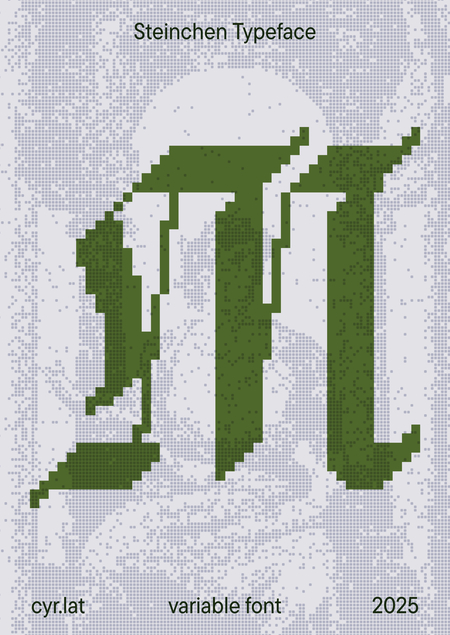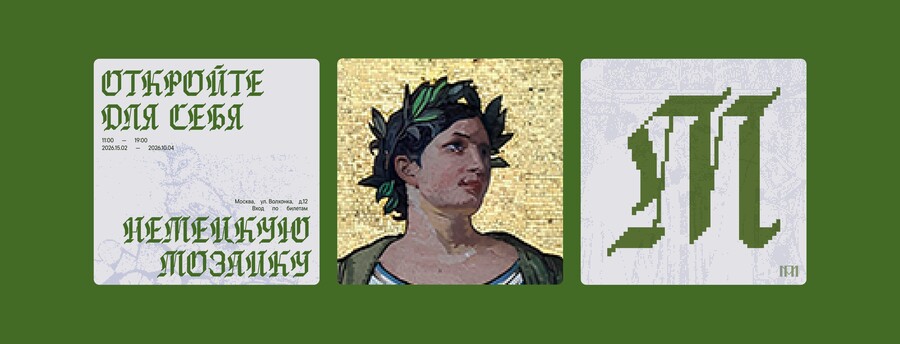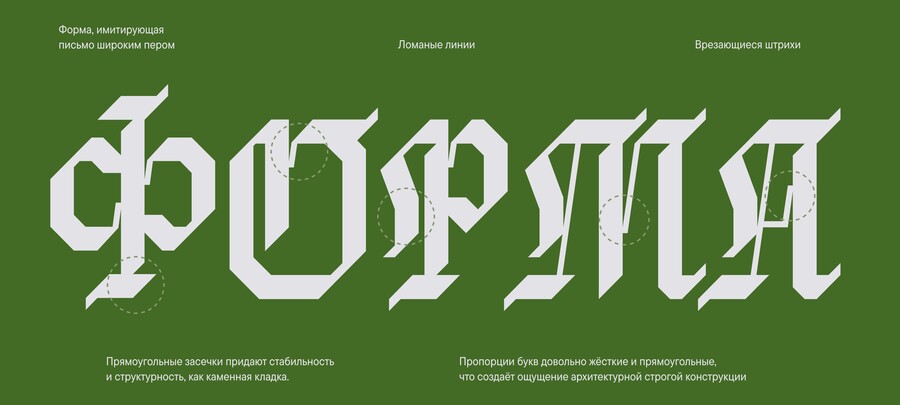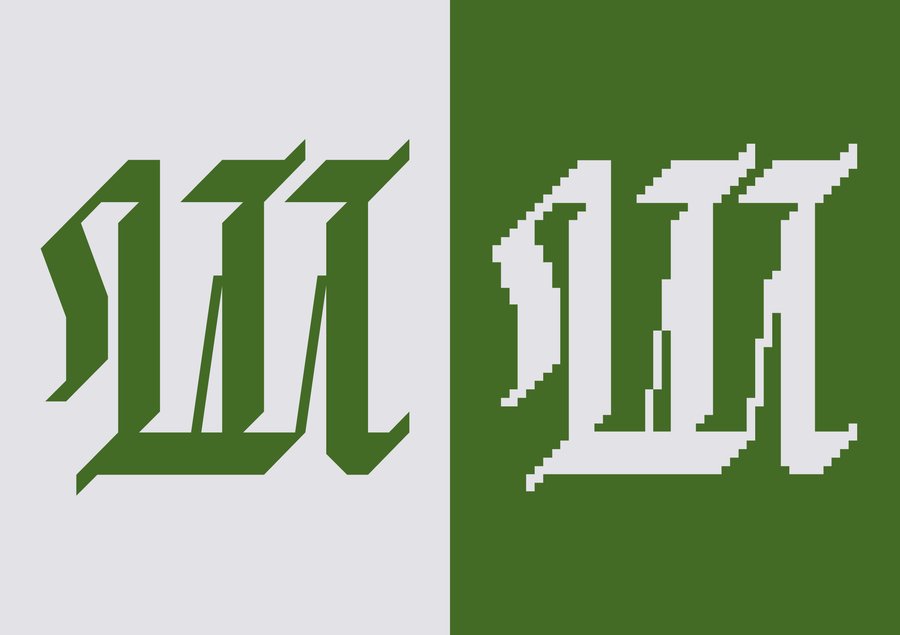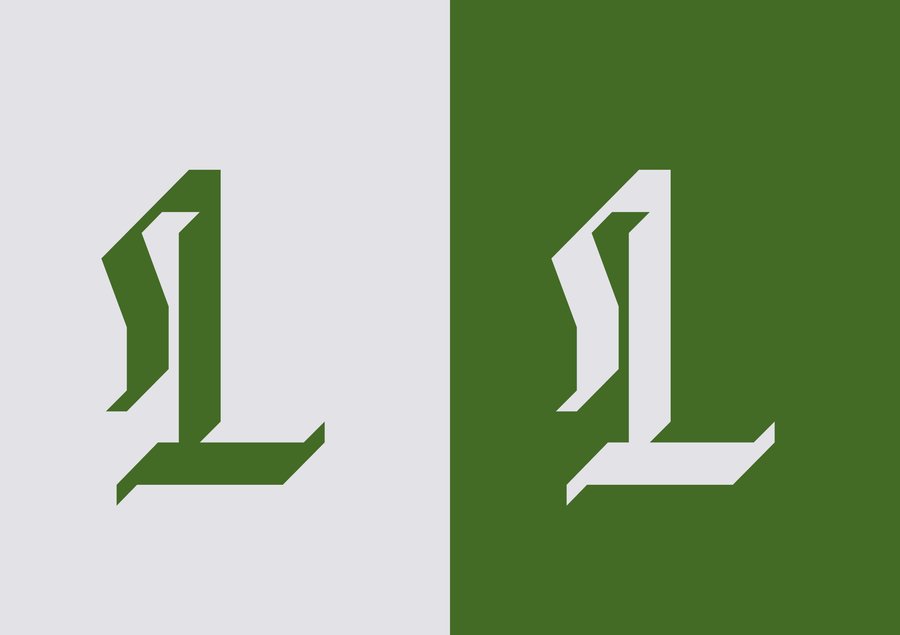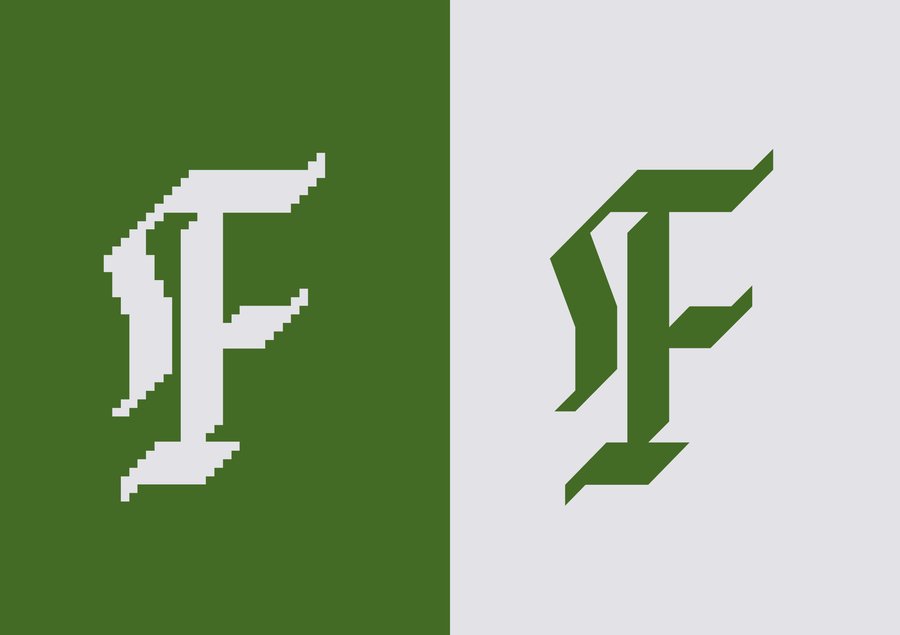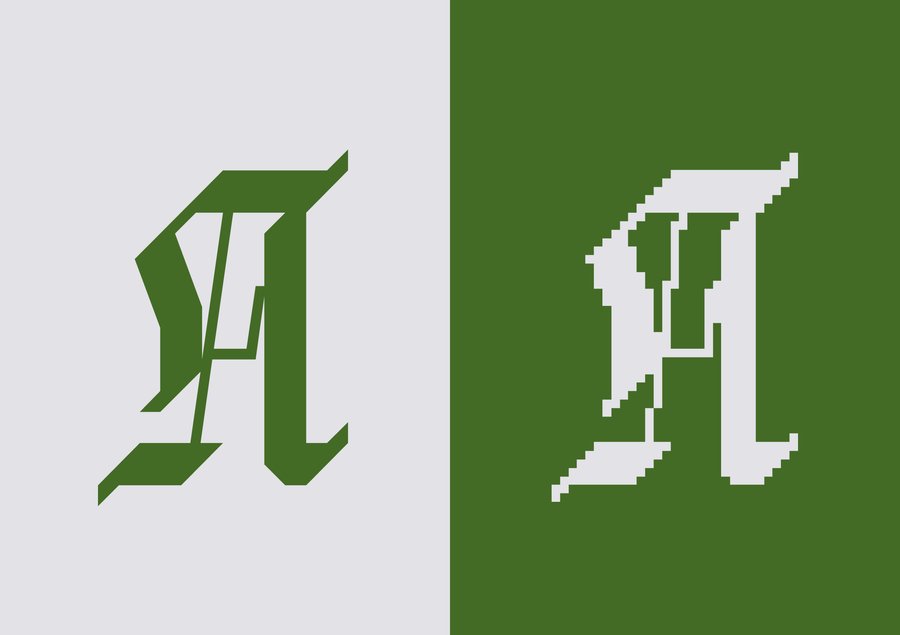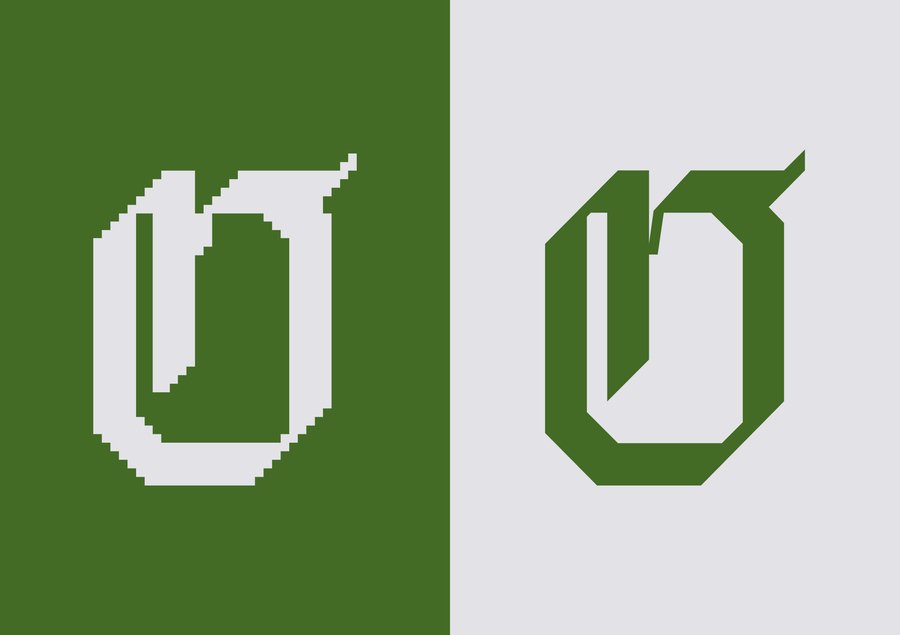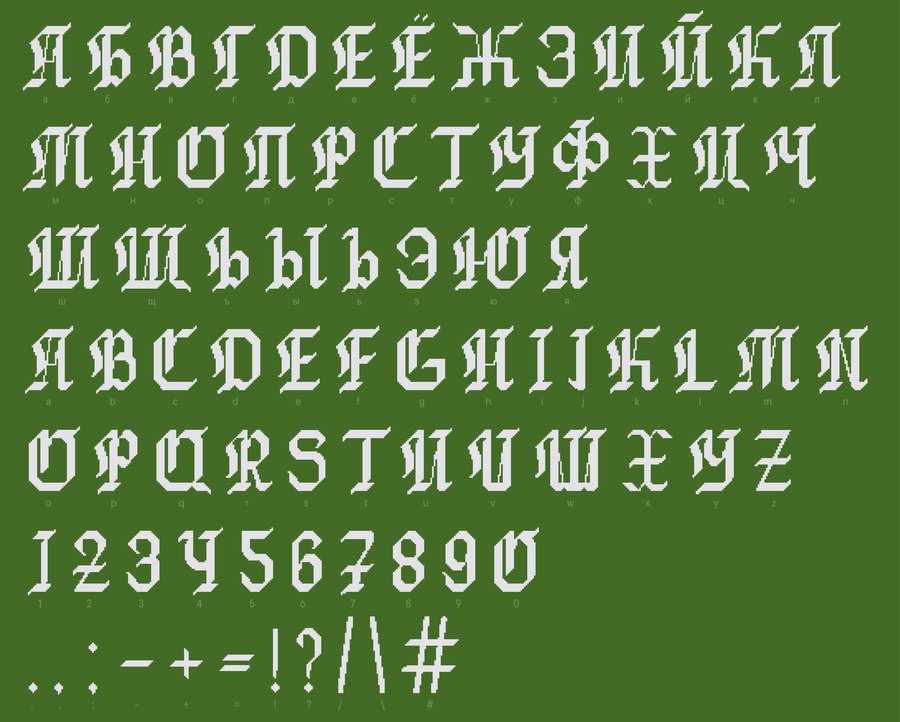
Steinchen Typeface
Steinchen Typeface — это готический вариативный шрифт. Его формообразование строится на напряжённых вертикалях и рубленых изломах — словно резцы каменщиков оставили след в букве.
Шрифт вдохновлен мозаикой и создан из фрагментов — tesserae — латинский термин, обозначающий
мозаичные кубики, из которых складывается мозаика.
Шрифт имеет два начертания
Полная касса